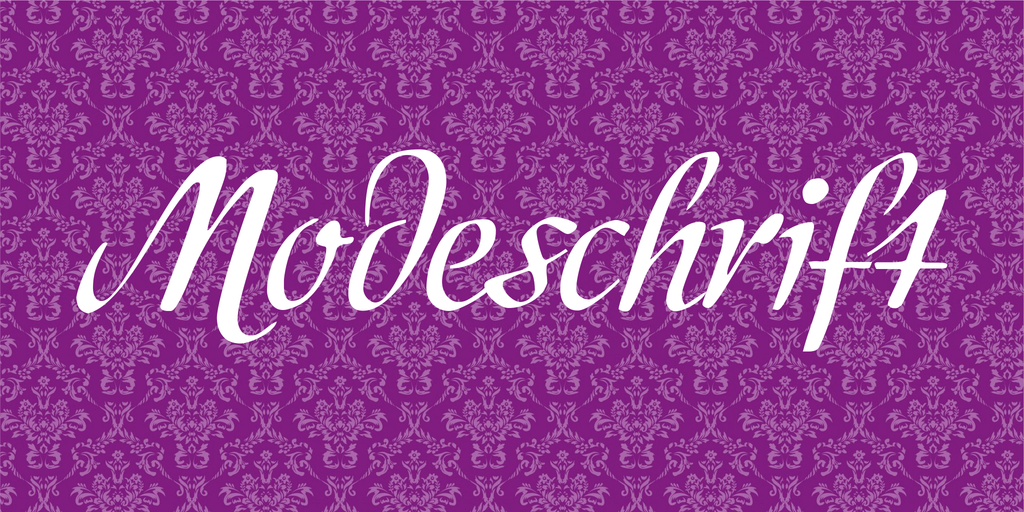
A fonte ‘Modeschrift Font’ é inspirada no estilo manuscrito de uma obra literária inédita do livro “Die Schriften des Malers” (O Escritor de Pintor), escrita por Walter Schenk e publicada pela Dr. Pfannenberg & Co. Esta fonte, criada pelo designer Hamilton, oferece um toque elegante e sofisticado ao texto, destacando-se no campo das fuentes manuscritas. Suas linhas suaves e acentos finos conferem um aspecto autêntico à sua origem literária, permitindo uma leitura envolvente que remete diretamente aos estilos tradicionais da escrita por pincel. Ideal para aqueles que buscam um texto com personalidade e estilo, esta fonte é perfeita para designers, editoras ou qualquer profissional interessado em adicionar um toque único a suas produções digitais.